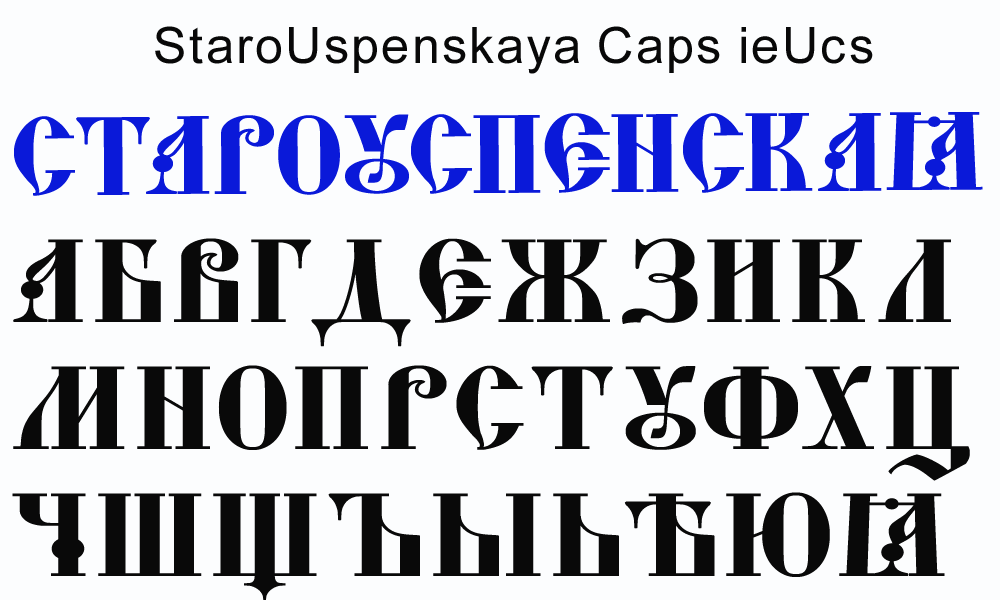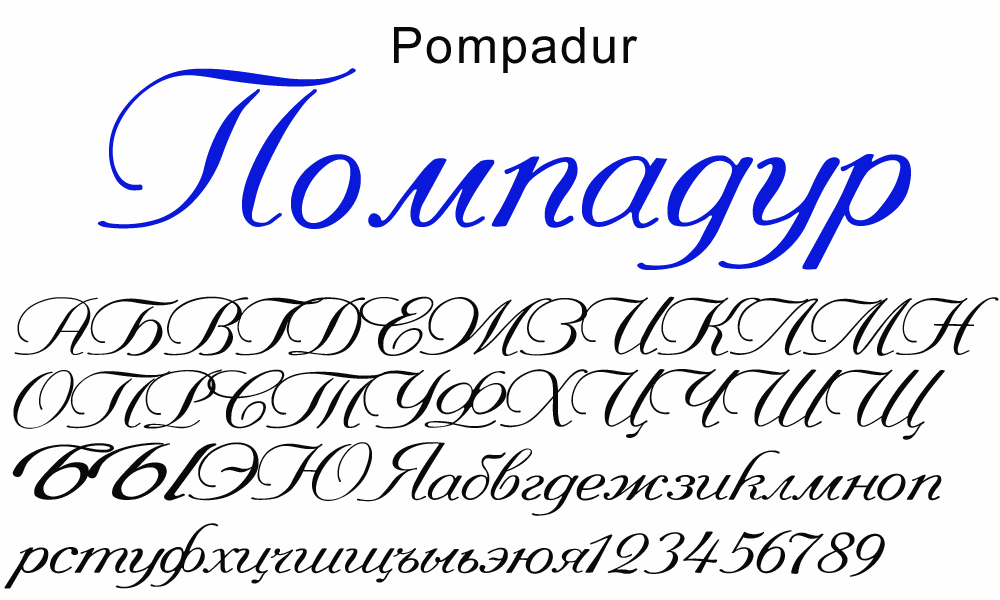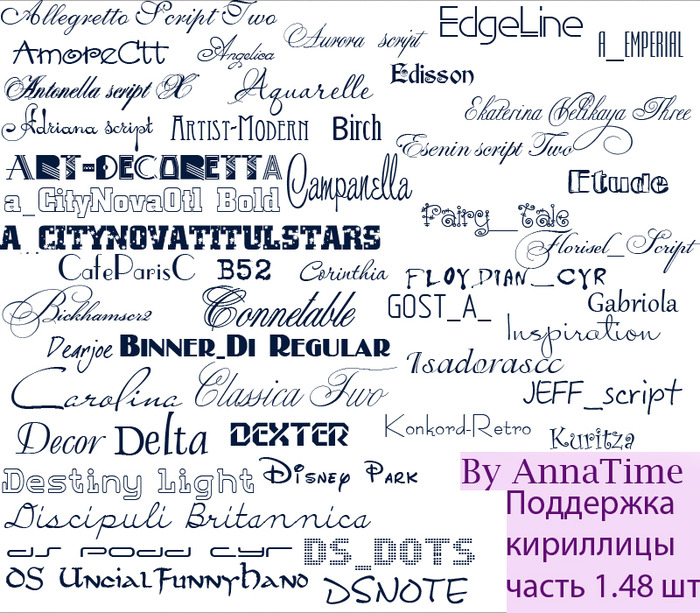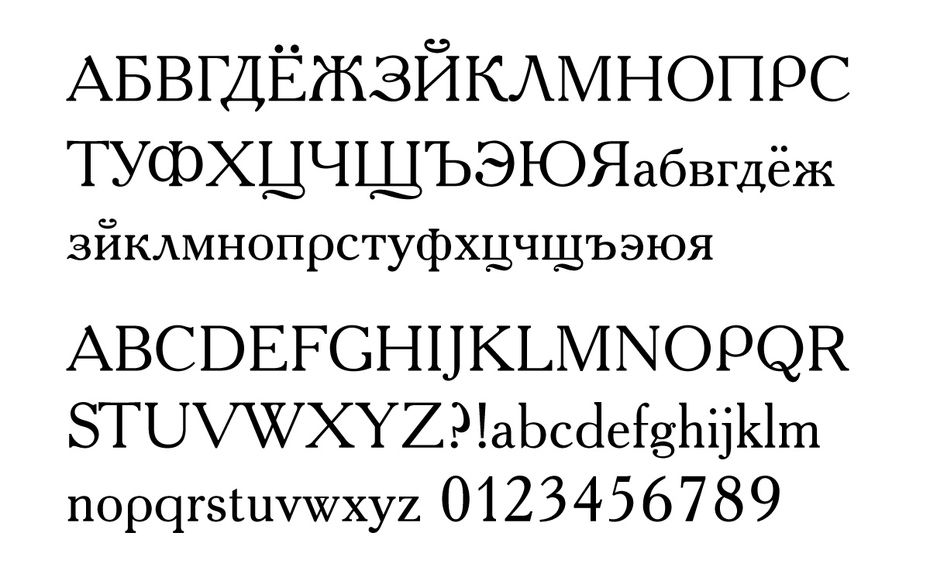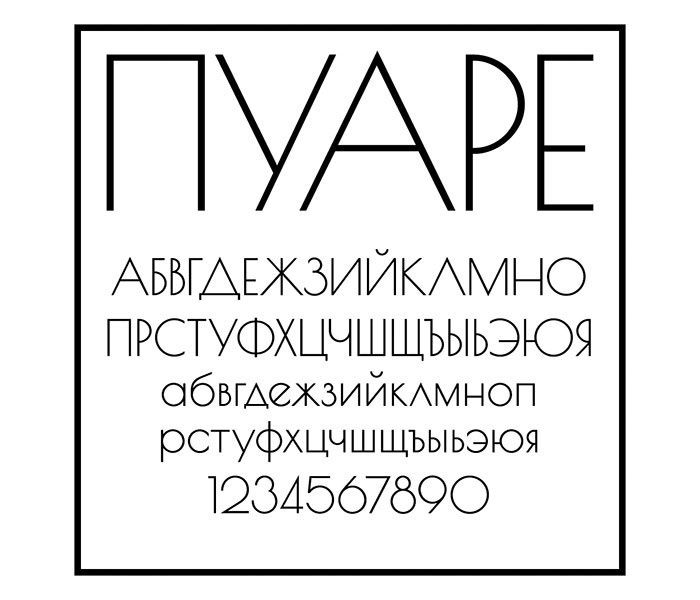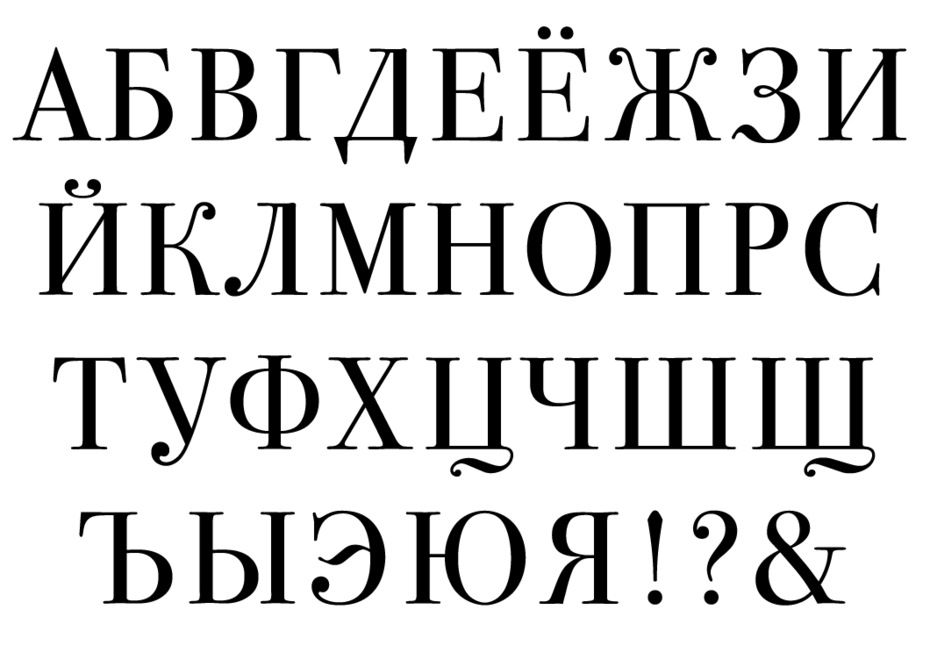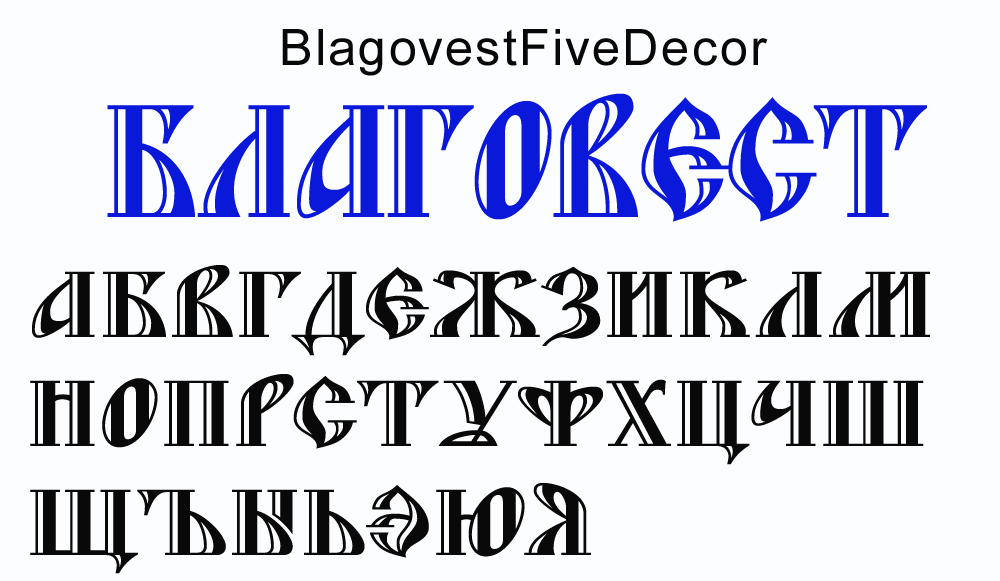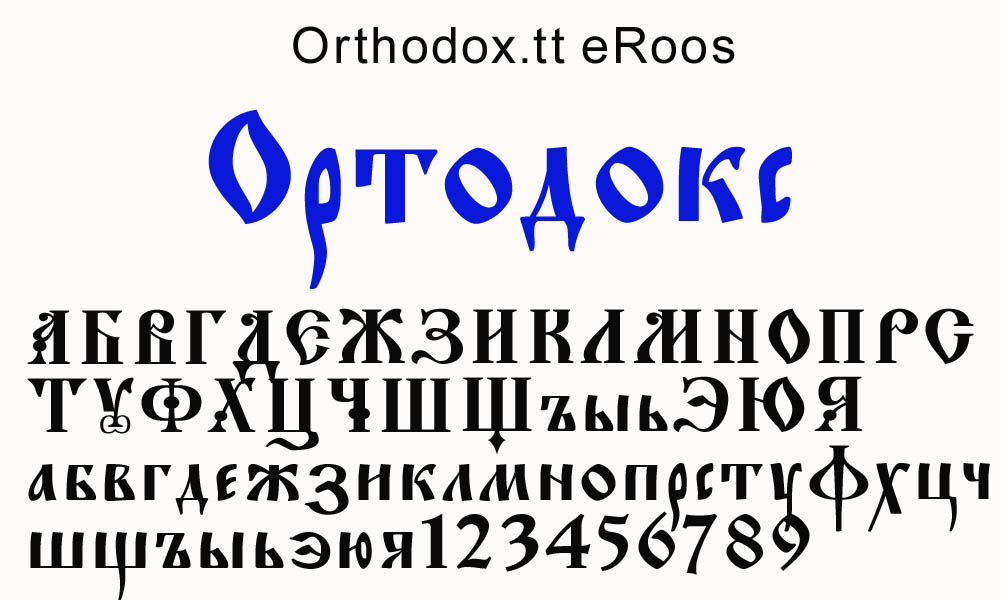
Шрифты русские для визиток: Шрифты для визиток как часть красивого дизайна
Шрифты для визиток как часть красивого дизайна
Способ подачи текстовой информации имеет огромное значение, когда речь идет о создании визитных карточек. Поэтому шрифты для визиток – часть дизайна, которая должна быть четко продумана. Далеко не всегда уместно экспериментировать с ними, подбирать витиеватые варианты, которые выглядят красиво, но могут затруднять читабельность текста промоматериалов.
Какой шрифт лучше использовать – вопрос, не имеющий однозначного, конкретного ответа. Во многом он зависит от дизайна изделий, направления деятельности человека или компании. Можно использовать фирменный шрифт из брендбука, если таковой имеется, но чаще приходится разрабатывать способ оформления, не опираясь на него.
Брендбук с шрифтами используемыми на визитке.Можно ли написать на визитке мелким, мелким шрифтом слоган компании?
В дизайне визиток допустимо применение микрошрифта для нанесения информации второстепенной важности – например, девиза компании.
Важность правильного выбора
Текстовая информация является важнейшей на пространстве промоматериалов.
Именно ради ее подачи создается оптимальный дизайн визитки. Благодаря ему в наиболее выигрышном свете она и преподносится. Способ оформления визитки должен подчеркивать текстовую информацию – личные, контактные данные, информация о направлении деятельности.
Выбор шрифтов – важная задача для дизайнера. Главное условие, которое к ним предъявляется – это должны быть хорошо читаемые шрифты. В противном случае получатель визитной карточки может попросту не захотеть вчитываться в текст, чтобы распознать и ознакомиться с его содержанием. Это сведет эффективность такого промоматериалы практически к нулю.
Часто на визитных карточках используется минимум графики или она не применяется вовсе. Например, многие деловые визитки содержат только логотип и текстовые элементы. В этом случае последние являются единственной и функциональной, и декорирующей составляющей. Это значит, что текст должен быть легко читаемым и красивым.
Визитка Яндекса в виде стрелки и корпоративными шрифтами.
Виды
Все виды начертания шрифтов делятся на две основные категории – без засечек (или рубленые) и с засечками. Самые популярные рубленые шрифты — Arial, Helvetica, Tahoma, Verdana, Pragmatica, Myriad, Helios. Это легко читаемые стили, которые часто применяют для деловых визитных карточек, требующих сдержанности и лаконичности. Самые известные шрифты с засечками – Times New Roman, Garamond, Bodoni. Бывают еще такие разновидности:
- Фигурные. К ним в первую очередь относятся рукописные варианты. Название шрифтов этой группы говорит само за себя – буквы имеют сходство с буквами, написанными от руки. Они имеют эффектный, красивый внешний вид, но их читабельность нельзя назвать идеальной. Для деловых визитных карточек такие стили обычно не используются, а вот представителям творческих профессий для своих промоматериалов применять их вполне можно. Исключение может составить случай, когда способы начертания для визиток подбираются в соответствие с фирменным стилем. Это касается и шрифта для логотипа визитки.
И даже в этой ситуации дизайнеры советуют для передачи важной информации использовать хорошо читаемые стили. Самые популярные из этой категории – Freestyle Script, Lobster, Pacifico, Nautilus Pompilius, Teddy Bear. К фигурным относятся и каллиграфические шрифты – красивые, эффектные буквы, которые, как и вся эта группа, характеризуются не самой лучшей читабельностью. - Винтажные. От них веет очарованием и особым шармом, но для деловых визиток компаний и людей, работающих в сфере инноваций, современных тенденций, они вряд ли подойдут. Но их могут использовать все, кто своими визитными карточками желает подчеркнуть традиции, многолетний опыт, вызывая тем самым доверие. Важно сочетание цвета фона и шрифта в визитках. Если используются винтажные начертания, то нужно применять приглушенные тона, цвет которых кажется выцветшим со временем. Самыми часто применяемыми и атмосферными вариантами этой группы являются Campton, Streetwear, Duma, Soria. Это незамысловатые, нейтральные начертания, которые не отличаются вычурностью, выглядят простыми, а при определенном дизайне – даже строгими.
- Мультяшные. Это «веселые», «игривые» буквы, но они не ассоциируются со стабильностью, надежностью, поэтому не способны вызывать доверие у получателей визитных карточек.
- Декоративные шрифты. Это прежде всего шрифты для дизайнеров, поскольку они разрабатываются как эксклюзивные начертания. Они могут быть фигурными, иметь засечки, быть выполненными в виде вензелей и с применением самых разных декоративных элементов. Бывают они стилизованными под гротеск, готику, ампир и многие другие стили. Со временем их эксклюзивность утрачивается, они перестают быть необычными, становятся узнаваемыми, а если их дизайн очень удачен, то и широко используемыми.
Часто на визитке можно увидеть сочетание разных стилей начертания. Например, Ф. И. О. могут быть напечатаны фигурным стилем, а контактная информация – вариантом без засечек. Если вы желаете совместить стили, такой вариант будет подходящим. Какое сочетание вы ни подобрали бы, учитывайте важное правило – на визитной карточке должно быть максимум два шрифта.
Размер шрифта
Подбирая его, снова нужно вспомнить о главном правиле – текст должен быть читаемым. Получатель визитной карточки не должен присматриваться к тексту с лупой в попытке разглядеть его содержание.
Выбор правильного шрифта для вашей визитной карточки может быть долгим и трудным процессом. Выбор правильного шрифта может помочь вам легко передать образ вашего бренда. Эти шрифты также могут определить, насколько повседневной или профессиональной будет презентация вашего бренда. В дальнейшем вы можете использовать эту информацию для создания визитной карточки, которая будет выделяться на фоне остальных.